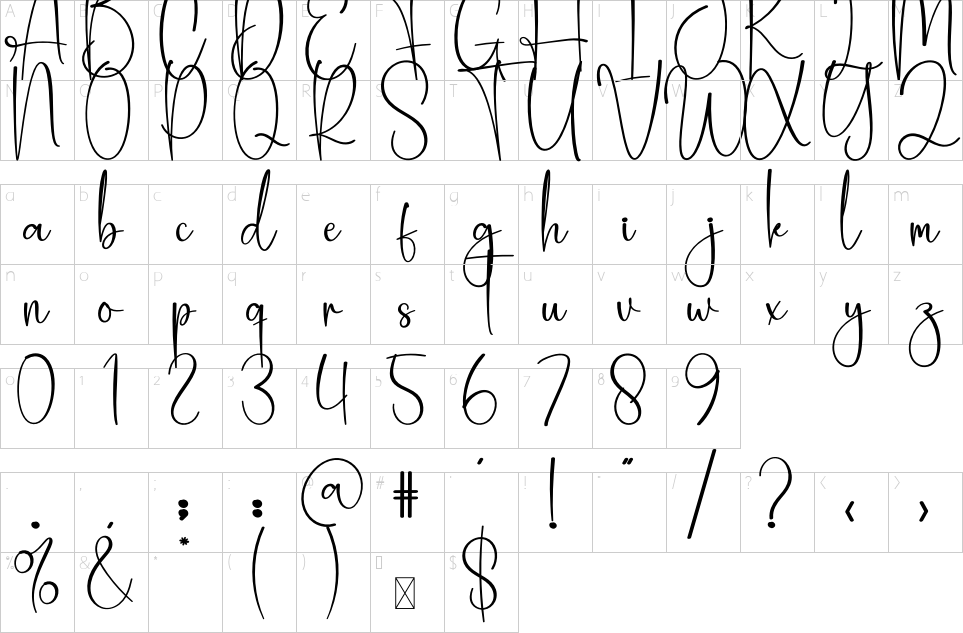
A Moonstone Font é uma elegante e suave fonte gráfica que se destaca na categoria de fontes gratuitas. Desenvolvida por scratchones, esta fonte possui um design minimalista e moderno que se adapta perfeitamente para textos em sites, blogs e páginas web. Seu estilo minimalista e sua facilidade de uso tornam a Moonstone uma escolha ótima para designers e criadores de conteúdo em busca de uma fonte de alta qualidade sem ter que pagar. Com apenas 385 downloads, a Moonstone Font é uma fonte rara e valiosa para aqueles que buscam um estilo elegante e versátil. Instale-a em seu computador e experimente a diferença que ela pode fazer em seus designs.